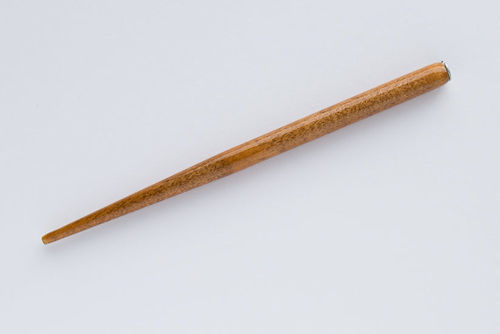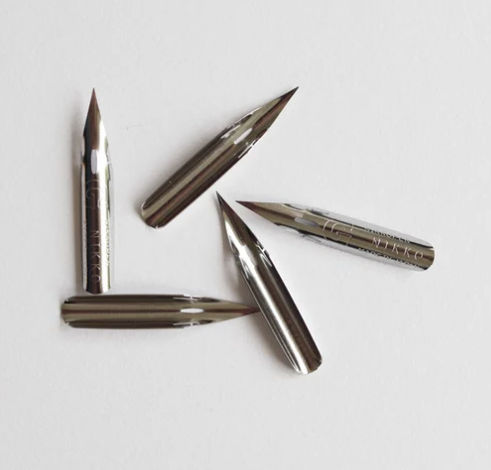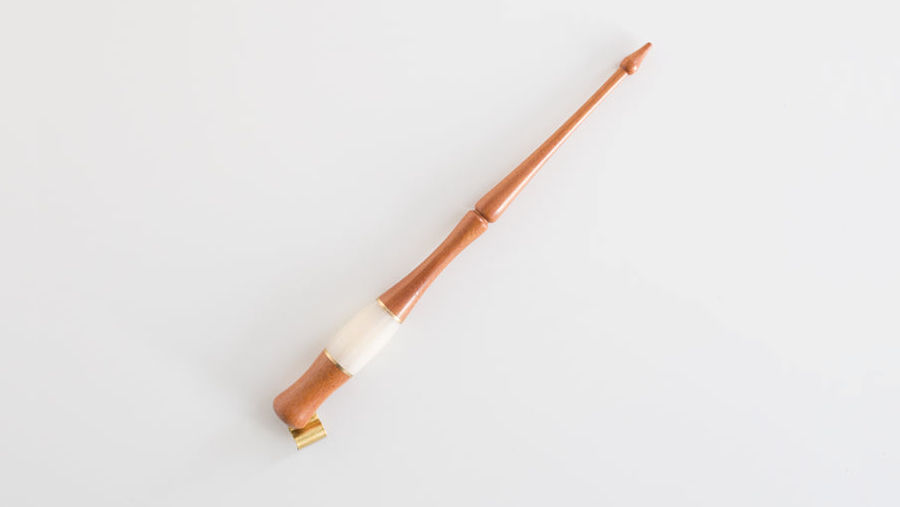
Vandaag het internet geraadpleegd,  de welke ik best zou nemen. Op verschillende websites werd gezegd om meteen een oblique penhouder (schuine kalligrafiepen) te kiezen als men voor de copperplate-stijl gaat.
De copperplate wordt geschreven met een spitse pen, het is een sierlijk schrift met fijne en dikke lijnen.
Dit is een voorbeeld van een copperplate schrift.
Het is wel een uitdaging zegt men,  dan denk ik wel meteen, stel dat het niet goed gaat, ben ik dan niet beter met een rechte pen om te beginnen? Of eerst het ene proberen dan het andere?
Zelf ben ik van mening om niet de goedkoopste te nemen, 1 ding ben ik wel zeker, het moet hout zijn. Licht in de hand, en mijn handen gaan er niet van zweten. Al zeker geen plastiek.
Uiteindelijk ben ik bij webshop Splendith uitgekomen. Ik zag meteen 1 staan, oblique hout, een degelijke penhouder, uiteindelijk in het mandje gezet tesamen met een rechte penhouder ook 1 van hout.
Een paar nibs, Nikko G, bij en inkt. De inkt die ik wou was uitverkocht. Gelukkig hebben ze me per mail kunnen helpen welke ik best zou nemen. Het werd Dr. Ph. Martin’s Hicarb Ink. Eigenlijk wilde ik Kuretaki, maar helaas overal uitverkocht.
Inkt Dr. Ph. Martin Hicarb Waterproof India Ink
Wat zijn nibs? Dit zijn metalen penpunten om mee te schrijven die men in de penhouder schuift.
Tot hier mijn tussenstop, ondertussen oefen ik rustig verder met mijn brushpen.